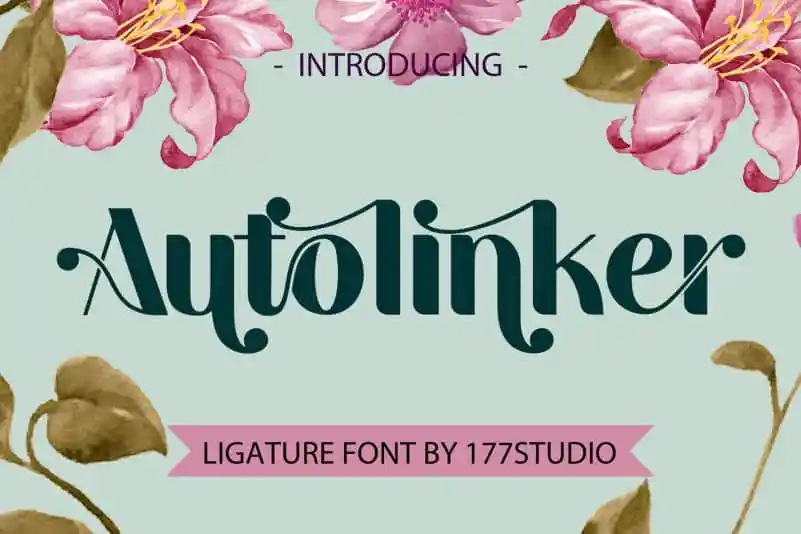
Autolinker – Fancy Ligature Font – Download Grátis
A fonte Autolinker – Fancy Ligature Font é uma combinação perfeita de contemporaneidade e elegância, com sua proporção equilibrada e atraentes ligaturas. Introduzida para projetos que exige destaque e sofisticação, esta fonte de display oferece contraste moderado, tornando-a ideal para uma variedade de aplicativos gráficos como branding, logomarca, designs de casamento, postagens nas redes sociais, anúncios, embalagem de produtos, design de produto, etiquetas, fotografia, marca d’água, convites e papelaria. Sua grande vantagem é a legibilidade alta em qualquer aplicação que precise de uma letra clara e agradável aos olhos, tornando-a uma escolha segura para projetos profissionais e pessoais.